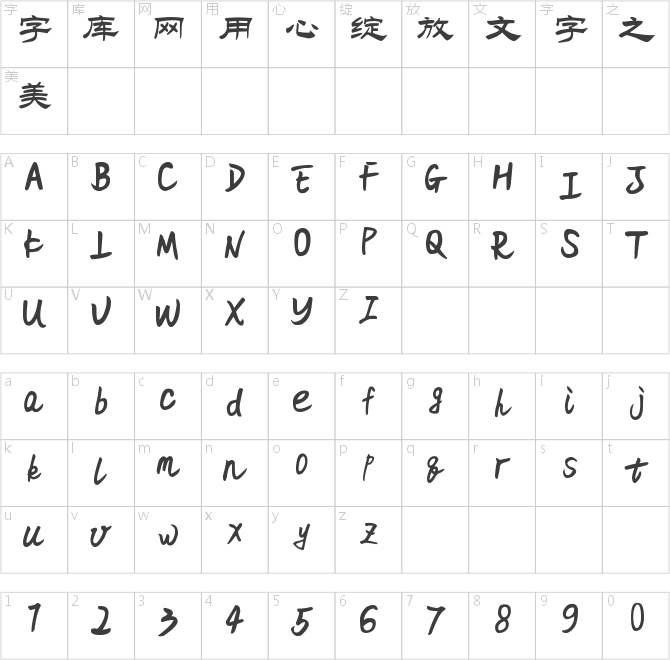
字体名称: 鼎猎客家体
鼎猎客家体
爨体字所具有的古韵、浑厚、拙朴特质,与客家文化相互交融。
由此碰撞出专属于客家人的鼎猎客家体。鼎猎客家体(作品登记证书登记号:陕作登字-2024-F-00013784),是一套根据简体中文汉字编码国家标准(GB2312编码)设计的字体,并在此基础上一共设计了6789个简体汉字。
鼎猎客家体为一款原创字体,具有其独特的字形风格,适用于广告、书籍、海报等多个场合。其中,特别增加了客家话专属汉字数十个。